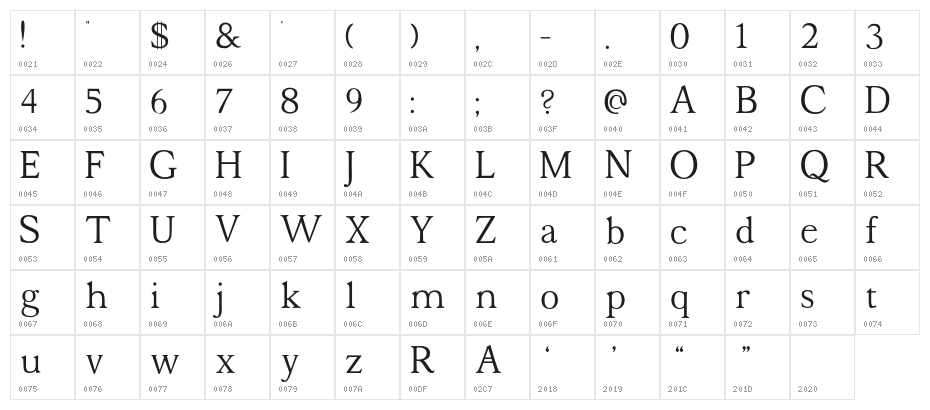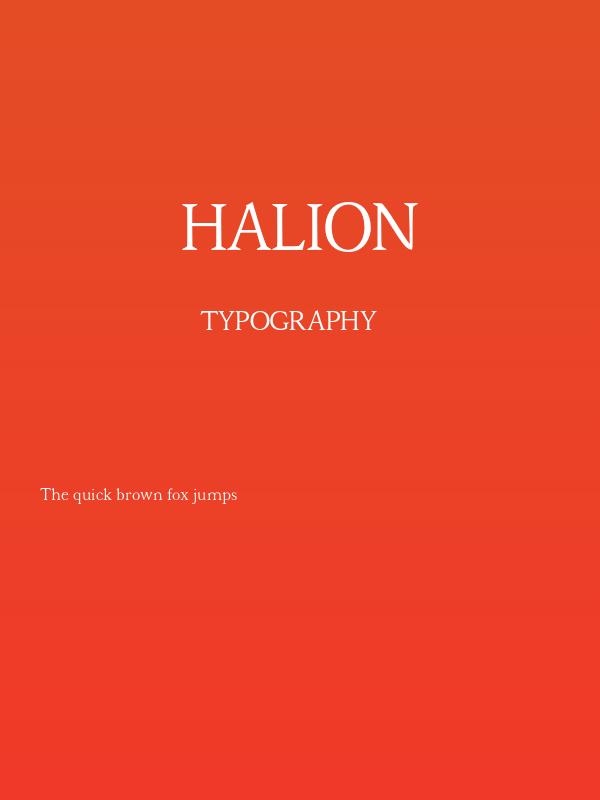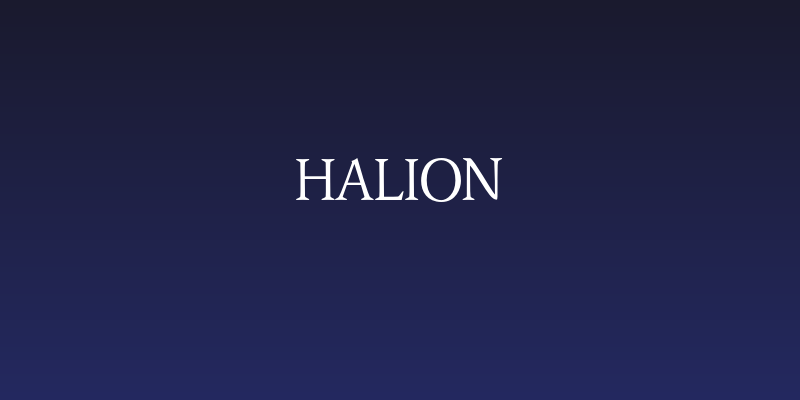
Halion Font
✎ Serif
| Kategorien | Serif |
| Gesamtstil | Classic |
| Anwendungsfall | Headlines, Body text, Logos |
| Vorgeschlagene Projekte | Ideal for book covers, editorial design, formal invitations, and branding projects that require a touch of elegance. |